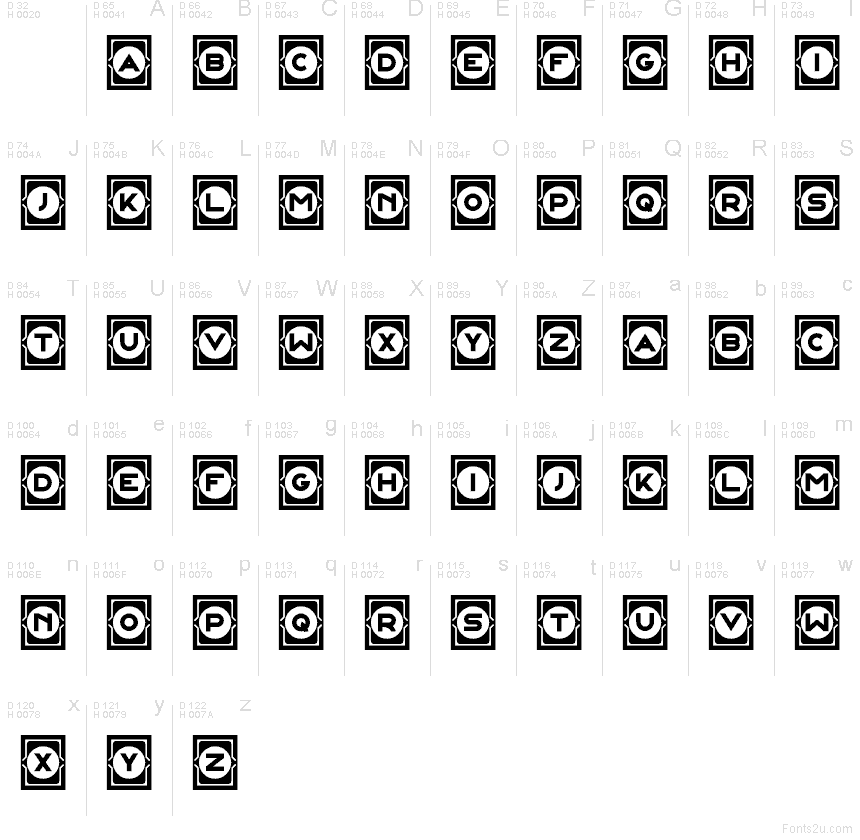
Concave Frames Retro de Vladimir Nikolic est une police d'affichage rétro gratuite, construite autour de lettres géométriques audacieuses inscrites dans des cadres. Le mélange répétitif de bordures carrées, de centres circulaires et de petites encoches vers l'intérieur confère à cette police une esthétique typique de la signalétique du milieu du XXe siècle, décorative sans être trop chargée.
Elle s'adapte parfaitement à l'image de marque des diners, aux affiches style arcade, au packaging, aux génériques, aux flyers d'événements et aux titres courts où le rythme des encadrements fait une partie du travail pour vous. En tant que police gratuite, elle est idéale pour les mises en page courtes, notamment les logos ou les en-têtes qui ont besoin de ce look modulaire, façon badge, pour dynamiser la composition.